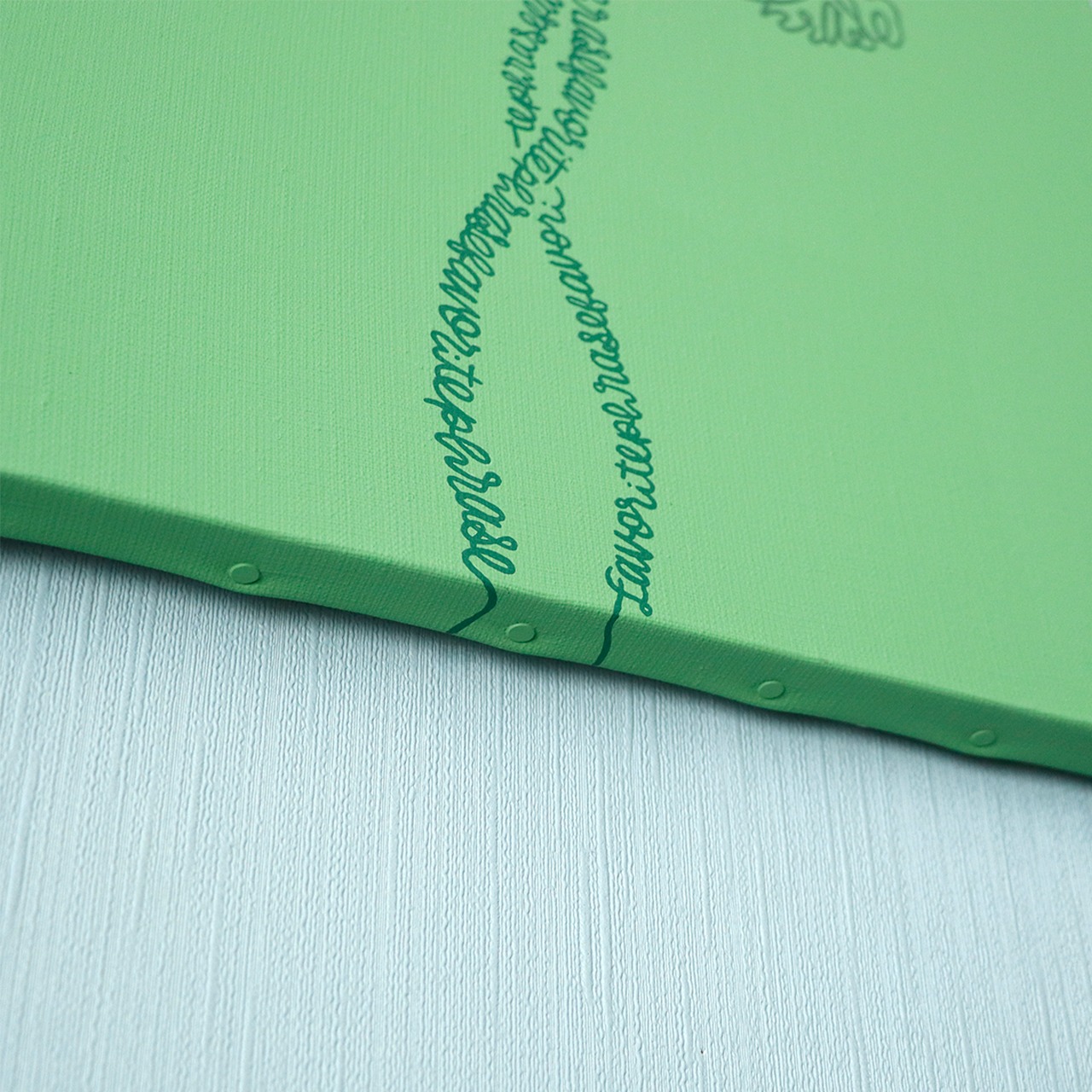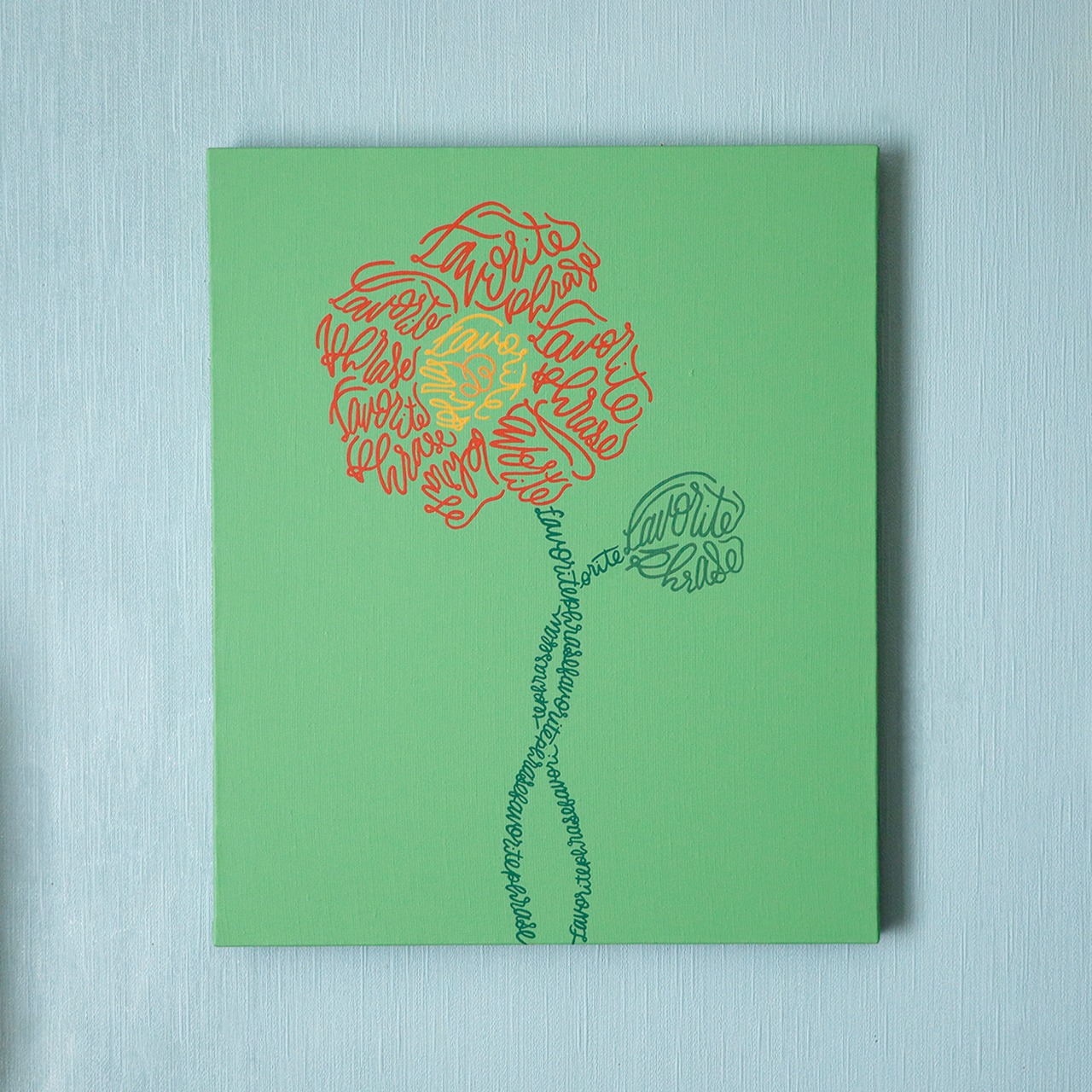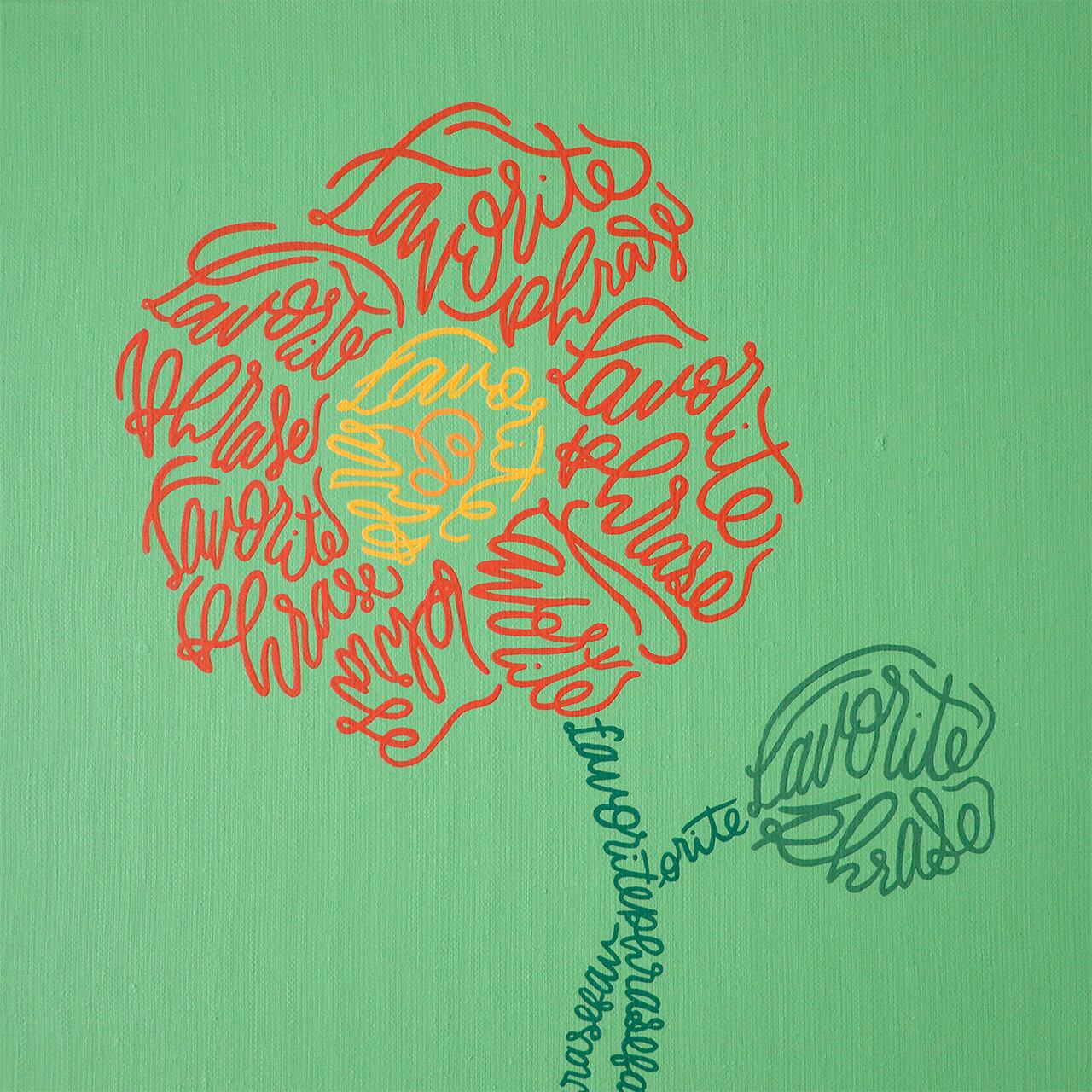
words flower 018 / favorite phrase2
words flower 018
favorite phrase2
2026年4月に開催した個展「favorite phrase2」のメインビジュアルで描いた文字の花です。
モデルの花はアイスランドポピー。
どっしりとした花とクネクネした茎、咲くのか咲かないのかドキドキな蕾(咲きませんでした)を
「favorite phrase」の文字に載せています。